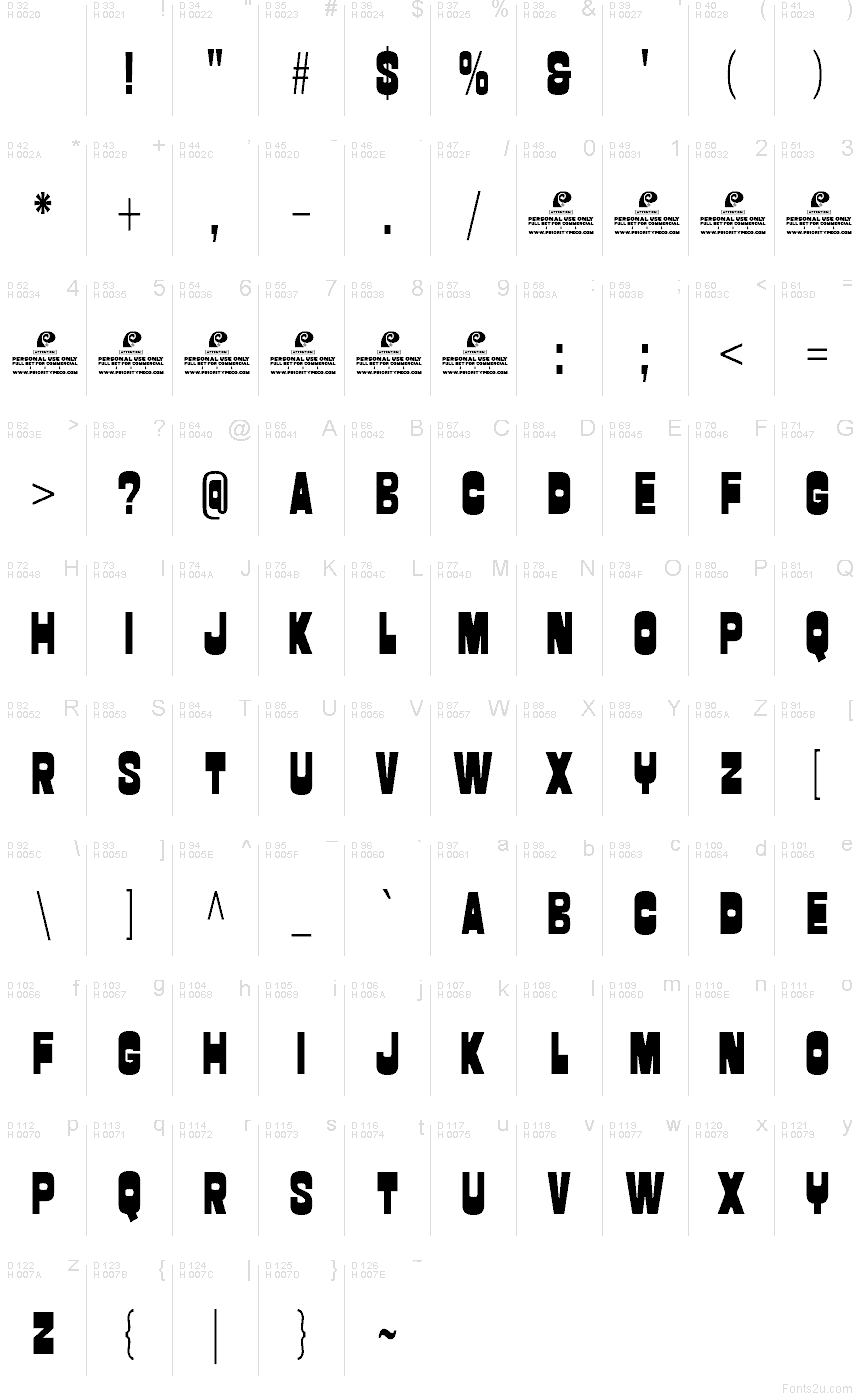
PC Merchis Condensed von Prioritype Co. ist eine kostenlose, schwungvolle Groovy-Display-Schrift mit hoch aufragenden, dicht gesetzten Versalien und einem markanten Black-Gewicht. Breite vertikale Striche treffen auf abgerundete Ecken und erzeugen eine kompakte Silhouette mit leicht aufgeblasenem Charakter. Kleine, runde Öffnungen schärfen ihre grafische Wirkung.
Der vom Showcard-Stil der 1970er-Jahre inspirierte Look eignet sich hervorragend für Musikplakate, Festival-Brandings und Schallplattenhüllen. Die übergroßen Buchstabenformen können markante geometrische Illustrationen auf T-Shirts und Entertainment-Grafiken aufgreifen, sodass der Schriftzug zum eigenständigen Kunstwerk wird, anstatt nur eine neutrale Beschriftung zu sein.